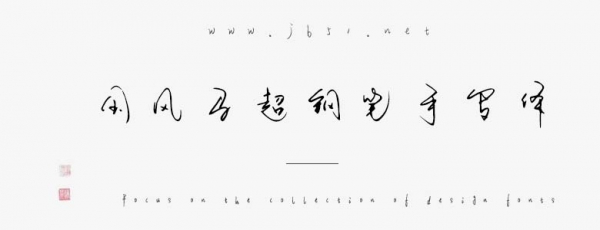
國風(fēng)馬超鋼筆手寫體是一款不錯(cuò)的藝術(shù)字體,字體筆觸略細(xì),具有很好的視覺感,適合應(yīng)用于藝術(shù)設(shè)計(jì)、平面宣傳設(shè)計(jì)、網(wǎng)頁設(shè)計(jì),書法字帖等領(lǐng)域,需要的朋友可以前來本站下載。